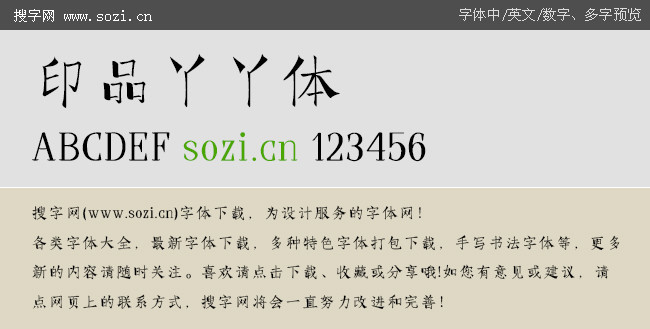
印品丫丫體
搜字網(wǎng)給大家提供一款印品丫丫體中文字體下載,印品丫丫體是一款適用性非常廣泛的中文字體,該字體連筆張弛有度,結(jié)體清麗優(yōu)美,大大削弱了視覺上的厚重感,識別度更強(qiáng),極具現(xiàn)代感。適用于海報設(shè)計、包裝設(shè)計、商業(yè)廣告等廣告設(shè)計。